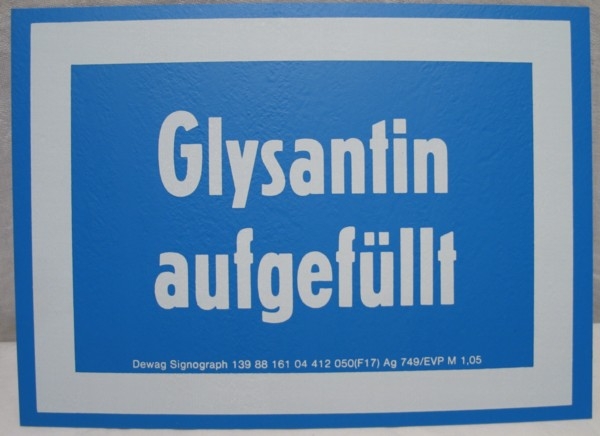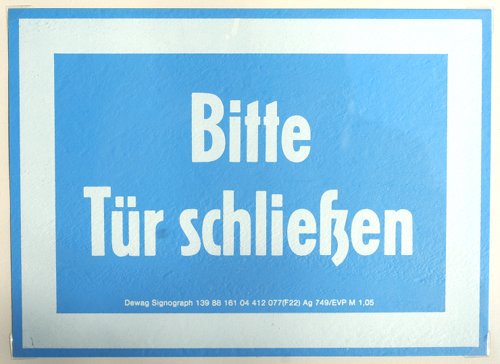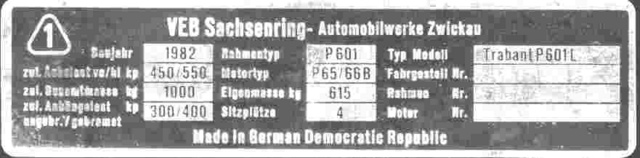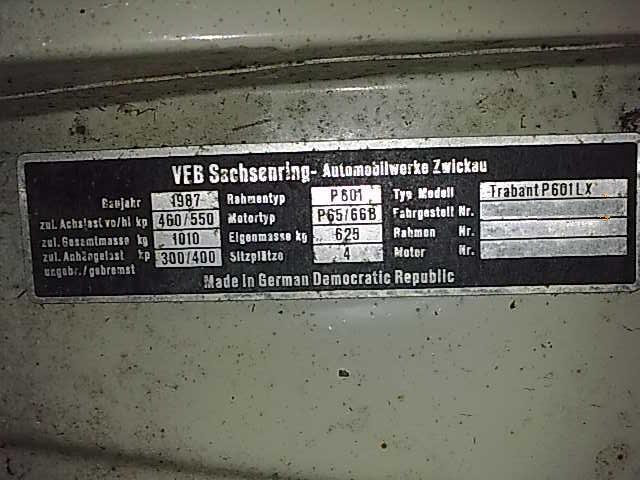
DDR-Hinweisschilder
Bei den Schildern handelt es sich um die
schmale halbfette Erbar Grotesk, 1929, Ludwig & Mayer, Frankfurt/M.
Es gab zu den Buchstaben a, A, M, N, V, W eine Variante.
ich suche etwas, was in dieses Thema zumindest halbwegs reinpasst. Und zwar
suche ich schon seit Ewigkeiten die Schriftart eines DDR-Typenschildes.
Es wäre schön, wenn mir jemand helfen könnte.
Falls die Bilder nicht gut genug sind, kümmere ich mich um bessere.
Aber vielleicht weiß es ja auch so schon jemand.
Zu der Zeit wurde das meiste, was nicht explizit Drucksachen waren, auch nicht mit Druckschriften im heutigen Sinne gemacht. Ich würde mir da nicht so viel Hoffnung machen, dass es genau diese Buchstabe heute als digitalen Font gibt.
Den mehr oder weniger kompletten Katalog der DDR-Druckschriften findest du hier: